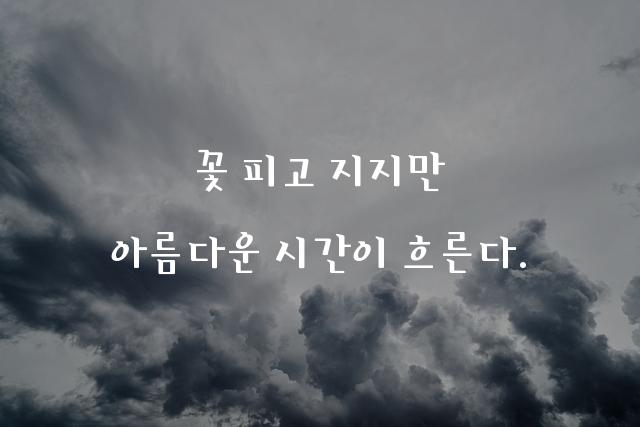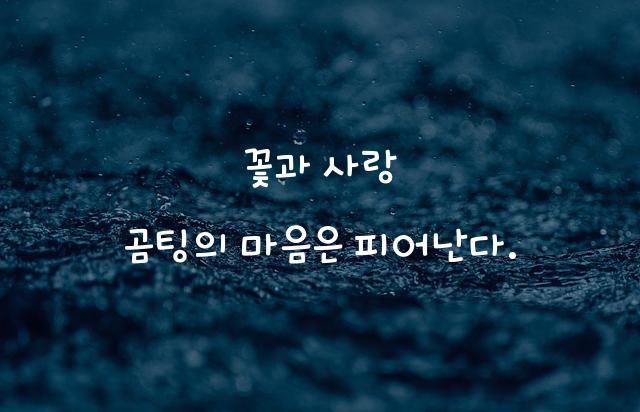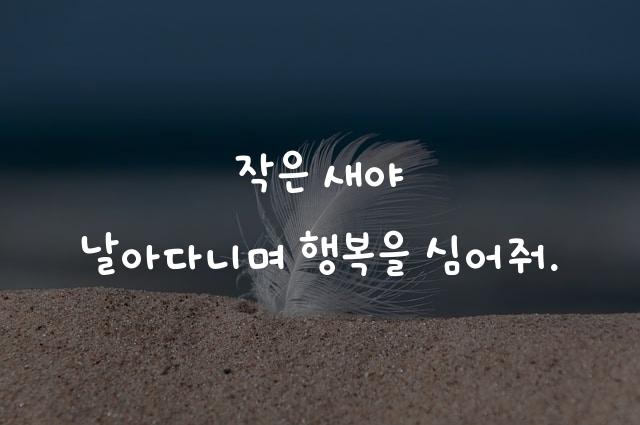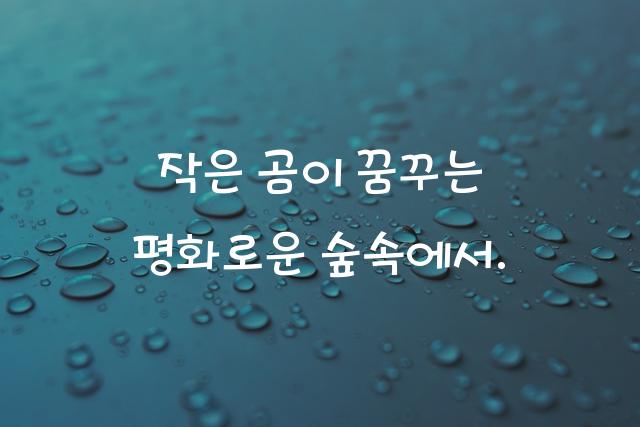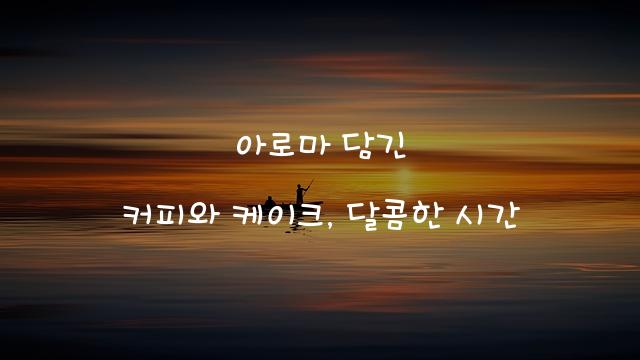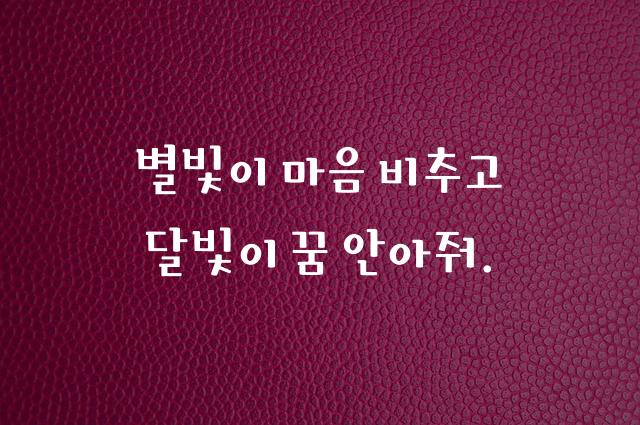
봉숭아틴트는 유토이미지에서 제작한 둥근 모양의 고딕 스타일 폰트입니다. 손글씨 같은 편안함과 친근감을 제공하여 따스한 인상을 남깁니다.
봉숭아틴트은(는)
기본 고딕, 둥근 스타일, 손글씨, 감성적인, 부드러움, 복실복실 계열의 생김새를 가지고 있으며
어린이 책, 인사말 카드, 일기/편지 등에서 자주 활용되며, 효과적인 메시지 전달에 적합합니다.
이 폰트는 문화/예술, 소매/유통, 유아/가족 분야에 잘 어울리며,
친근한, 귀여운, 재미있는 느낌을 담고 있는 것이 특징입니다.
이 폰트와 유사한 폰트로는 나눔손글씨 펜, 마포해변, 이롭게 바탕체 등이 있어요. 함께 비교해 보시면 좋습니다!